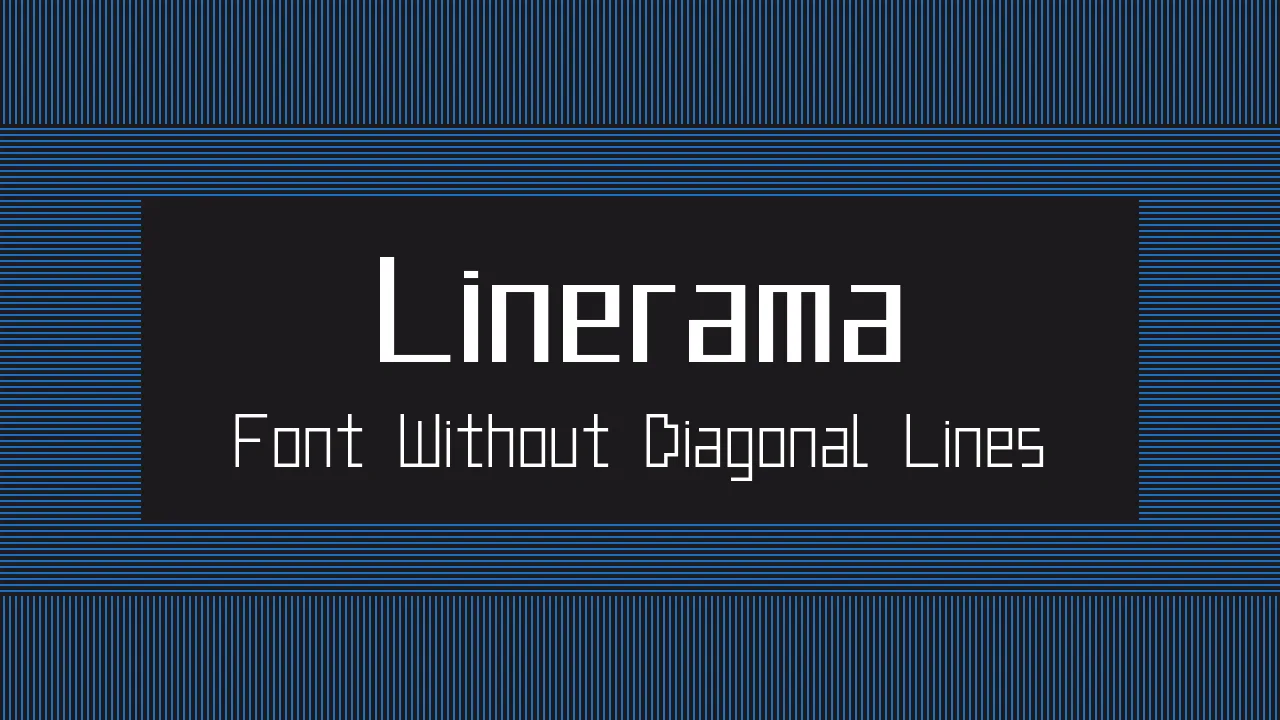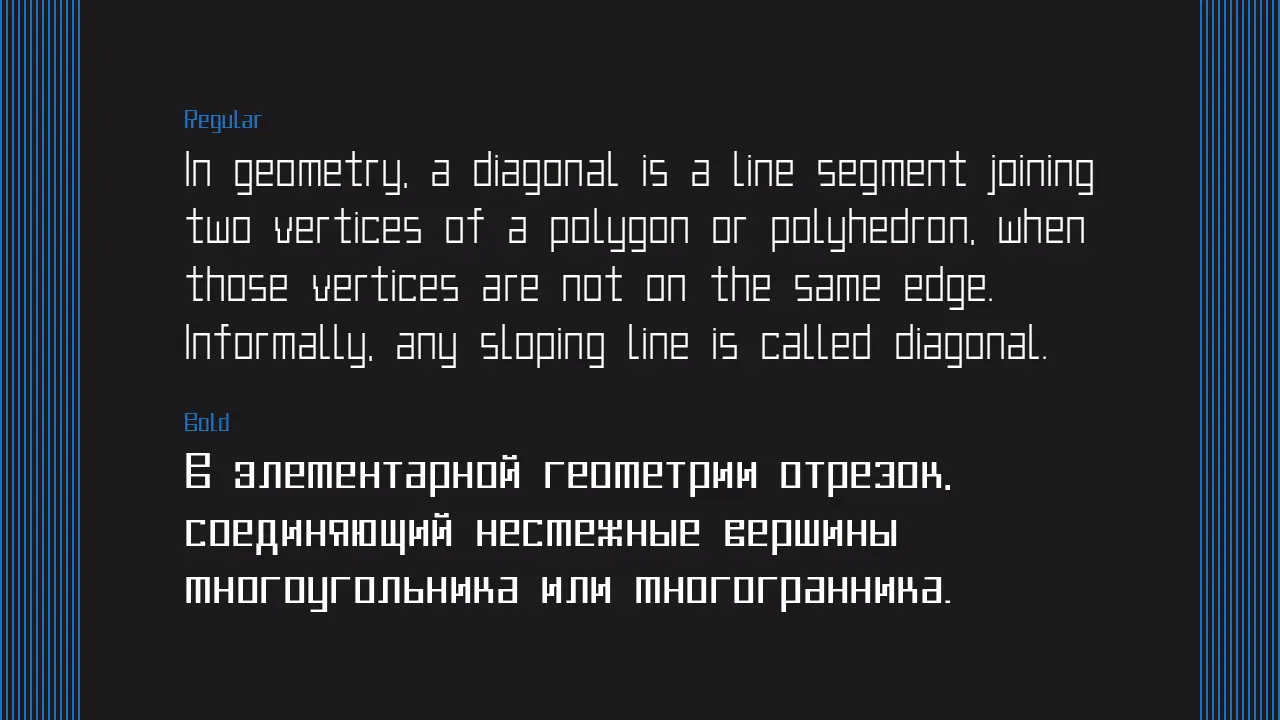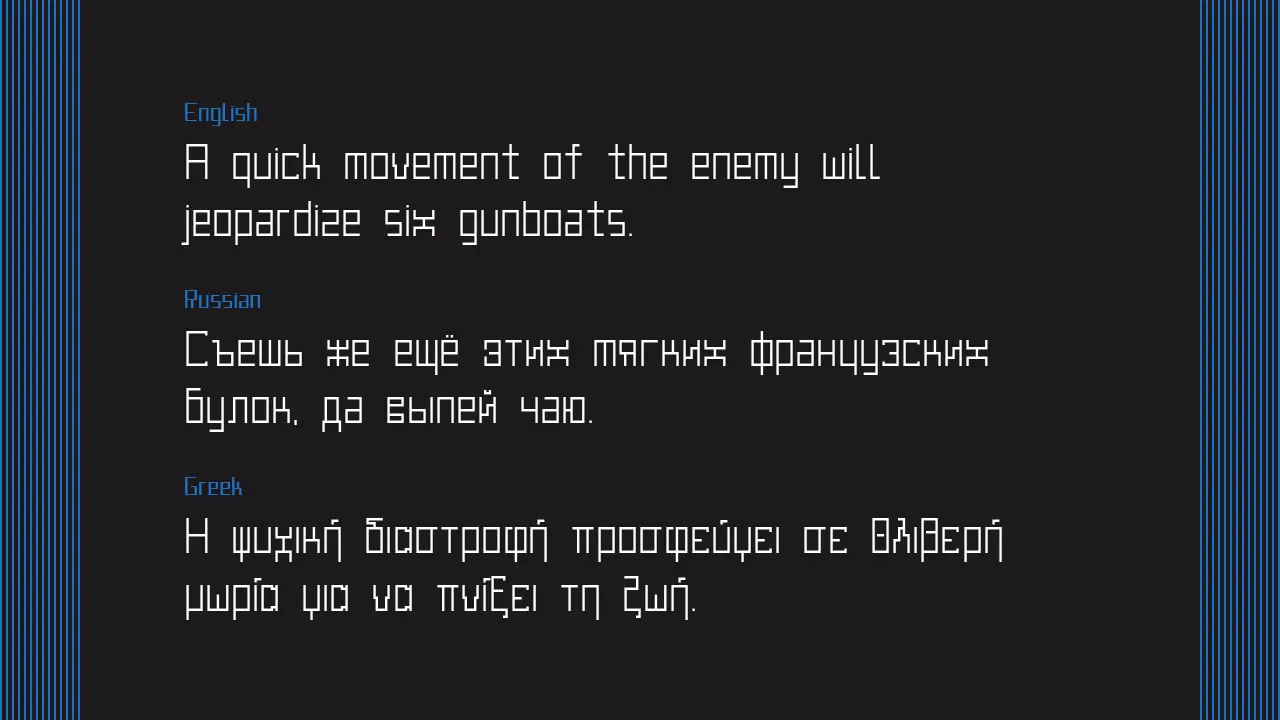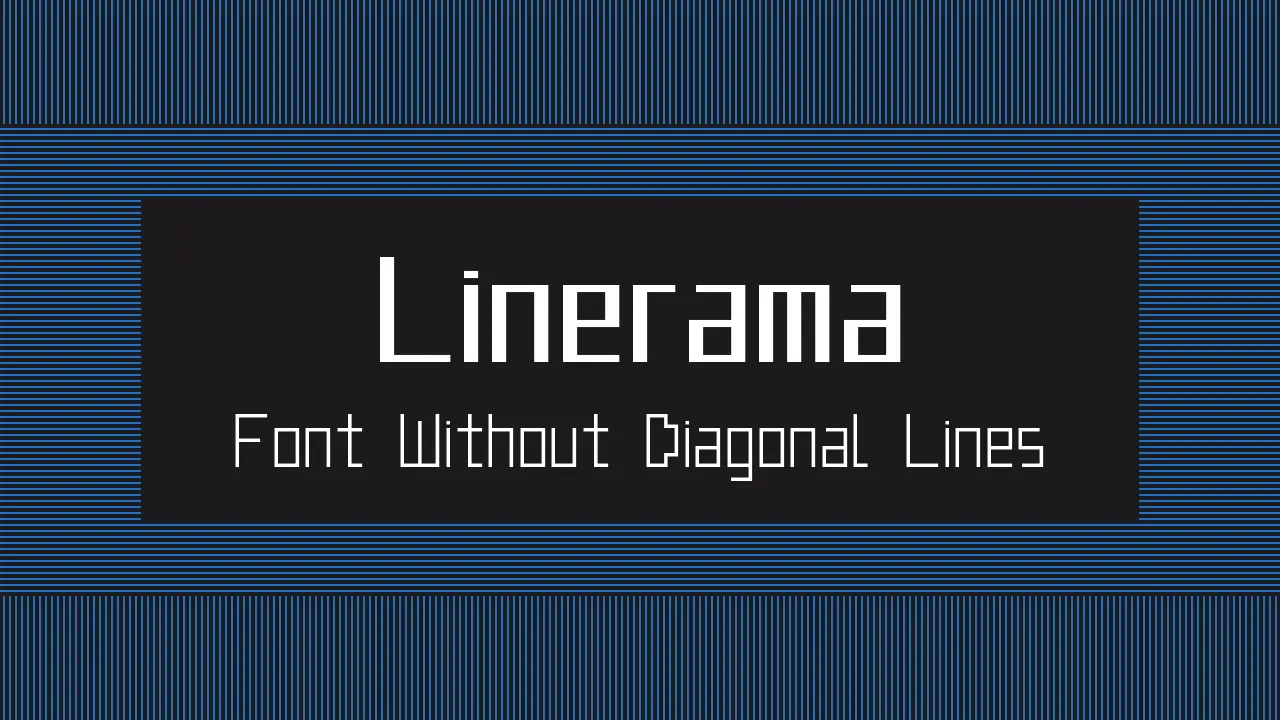
Linerama是一種沒有對角線的免費英文字體,根據SIL OFL協議發佈,包含 2 種樣式(Regular、Bold)和 815 個字形。支持 92 種語言(Aghem, Aja, 阿爾巴尼亞語, Aromanian, Asturian, Azeri, Basaa, Bashkir, 白俄羅斯, 布列塔尼語, 保加利亞語, 加泰羅尼亞語, Central Yambasa, 中文(拼音), Chuvash, 克羅地亞語, 捷克語, Dagbani, 丹麥語, Duala, 荷蘭語, 英語, 世界語,愛沙尼亞語、母羊語、Ewondo、芬蘭語、Fon、法語、Fula、Gagauz、德語、希臘語、匈牙利語、冰島語、伊博語、印度尼西亞語、愛爾蘭語、意大利語、Jula、Kabyle、Kako、哈薩克語、Khoekhoe、Koyra Chiini、Koyraboro Senni、吉爾吉斯語、拉科塔語、拉丁語、拉脫維亞語、立陶宛語、利沃尼亞語、馬賽語、馬其頓語、馬耳他語、馬普頓貢語、蒙古語、Ngiemboon、恩貢巴語、北薩米語、挪威語、波蘭語、葡萄牙語、裡夫語、羅馬尼亞語、俄語、蘇格蘭蓋爾語、塞爾維亞語、塞爾維亞語、Shawiya、Shilha、斯科爾特薩米語、斯洛伐克語、斯洛文尼亞語、西班牙語、瑞典語、他加祿語、韃靼語、特拉帕內克語、土耳其語、土庫曼語、烏克蘭語、烏茲別克語、瓦伊語、瓦爾瑟德語、威爾士語、西弗里斯蘭語、扎爾馬語、扎扎基語、祖魯語。)